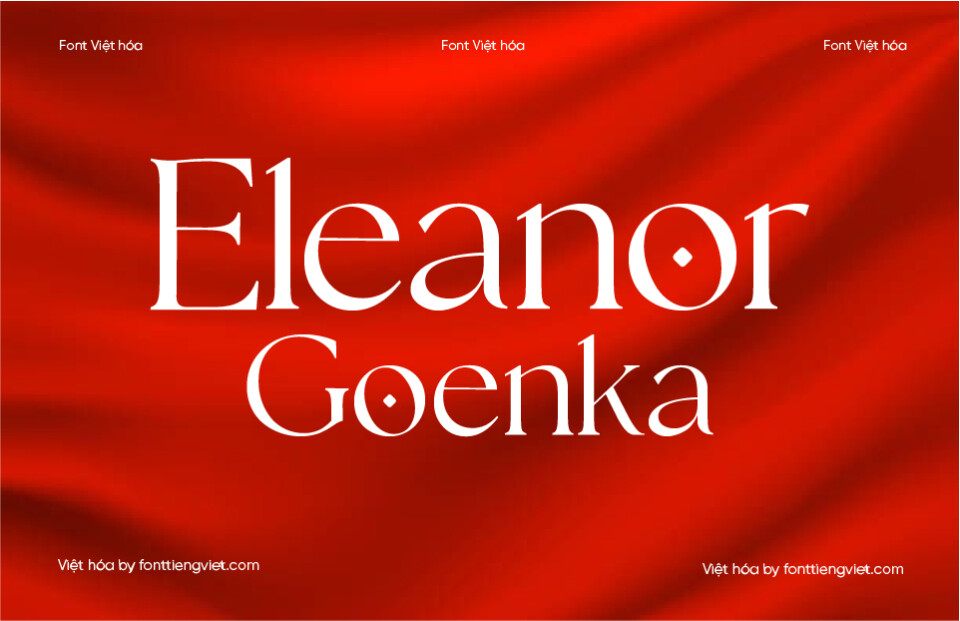
Font Việt hóa 1FTV VIP Eleanor Goenka
Giới thiệu về Font Việt hóa 1FTV VIP Eleanor Goenka trong thiết kế
Trong thế giới đồ họa hiện đại, việc tìm kiếm một bộ Font Miễn Phí chất lượng và hỗ trợ đầy đủ tiếng Việt luôn là ưu tiên hàng đầu của các nhà thiết kế. Font Việt hóa 1FTV VIP Eleanor Goenka nổi lên như một lựa chọn hoàn hảo cho những ai yêu thích phong cách sang trọng, tinh tế nhưng vẫn giữ được nét hiện đại. Đây là bộ font chữ thuộc dòng cao cấp, được đội ngũ 1FTV thực hiện việt hóa tỉ mỉ, giúp người dùng tại Việt Nam dễ dàng ứng dụng vào các dự án truyền thông, giáo dục và quảng cáo mà không lo lỗi font hay thiếu dấu. Với đường nét thanh mảnh kết hợp cùng các điểm nhấn uốn lượn đặc trưng, bộ font này tạo nên một cảm giác quý phái, rất phù hợp cho các thiết kế thiệp mời, bìa sách hoặc tiêu đề tạp chí chuyên nghiệp.
Đặc điểm nổi bật của Font Việt hóa 1FTV VIP Eleanor Goenka
Thiết kế thanh lịch và tính ứng dụng cao
Điểm mạnh nhất của Font Việt hóa 1FTV VIP Eleanor Goenka chính là cấu trúc ký tự cân đối và độ tương phản giữa các nét thanh nét đậm rất rõ ràng. Điều này giúp văn bản trở nên dễ đọc hơn ngay cả khi sử dụng ở kích thước nhỏ. Đối với các bạn học sinh và giáo viên, bộ font này là công cụ đắc lực để trang trí bài thuyết trình hoặc làm báo tường, giúp nội dung trở nên thu hút và có tính thẩm mỹ cao hơn. Sự kết hợp giữa nét cổ điển và hơi thở đương đại giúp nó không bị lỗi thời theo thời gian.
Tối ưu hóa cho tiếng Việt hoàn hảo
Một vấn đề thường gặp khi sử dụng font ngoại nhập là các ký tự có dấu như “ă, ê, ơ, ư” thường bị nhảy lỗi hoặc không đồng nhất về kiểu dáng. Tuy nhiên, với phiên bản Font Việt hóa 1FTV VIP Eleanor Goenka, mọi rào cản về ngôn ngữ đã được loại bỏ. Từng dấu thanh đều được căn chỉnh vị trí chính xác, đảm bảo sự hài hòa tổng thể cho văn bản. Điều này đặc biệt quan trọng trong các ấn phẩm in ấn đòi hỏi sự chỉn chu tuyệt đối về mặt hình thức và ngữ pháp tiếng Việt.
Cách sử dụng Font Việt hóa 1FTV VIP Eleanor Goenka hiệu quả
Kết hợp font chữ trong các dự án đồ họa
Để phát huy tối đa vẻ đẹp của Font Việt hóa 1FTV VIP Eleanor Goenka, bạn nên kết hợp nó với các font chữ không chân (Sans-serif) đơn giản cho phần nội dung dài. Sự tương phản này sẽ giúp tiêu đề sử dụng Eleanor Goenka trở nên nổi bật và sang trọng hơn. Ngoài ra, việc sử dụng các tông màu pastel hoặc màu vàng đồng sẽ làm tăng thêm vẻ quý phái cho bộ font này. Đây là bí quyết giúp các bạn sinh viên ngành thiết kế tạo ra những portfolio ấn tượng chỉ với những thao tác đơn giản trên máy tính.
Kết luận về bộ Font Việt hóa 1FTV VIP Eleanor Goenka
Hy vọng rằng bộ Font Việt hóa 1FTV VIP Eleanor Goenka sẽ trở thành một người bạn đồng hành tin cậy trong quá trình sáng tạo của bạn. Với sự tinh tế trong từng đường nét và khả năng hiển thị tiếng Việt xuất sắc, đây chắc chắn là một tài nguyên không thể thiếu trong bộ sưu tập của bất kỳ ai yêu cái đẹp. Đừng quên truy cập thường xuyên để cập nhật thêm nhiều bộ Font Miễn Phí, Font Việt Hóa, Font Việt hóa 1FTV VIP Eleanor Goenka chất lượng khác nhằm làm phong phú thêm kho tàng thiết kế cá nhân của mình. Chúc bạn có những tác phẩm tuyệt vời và đầy cảm hứng với bộ font chữ đặc biệt này.